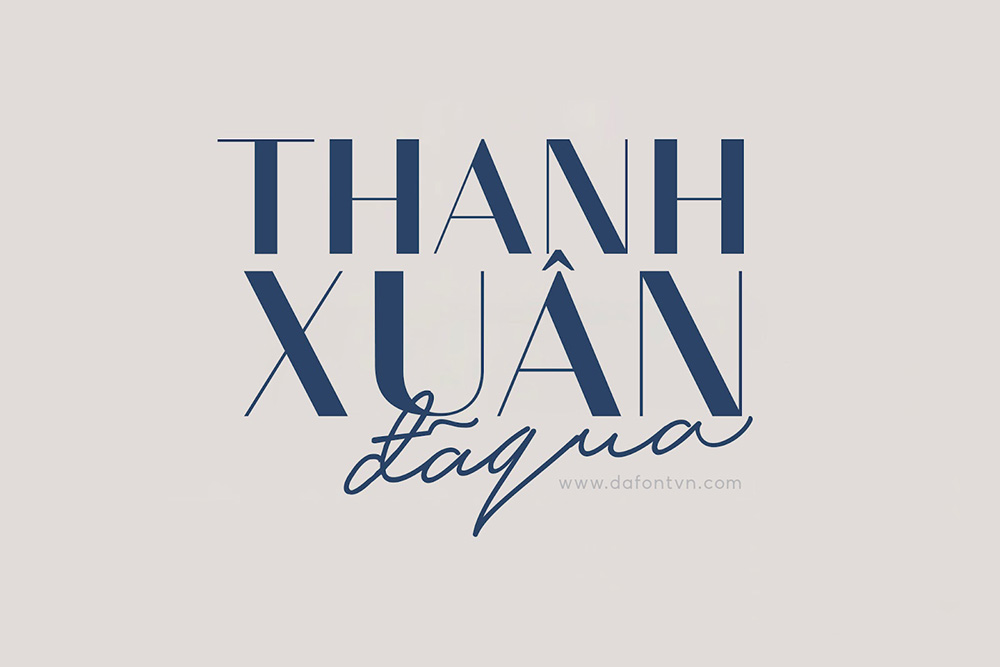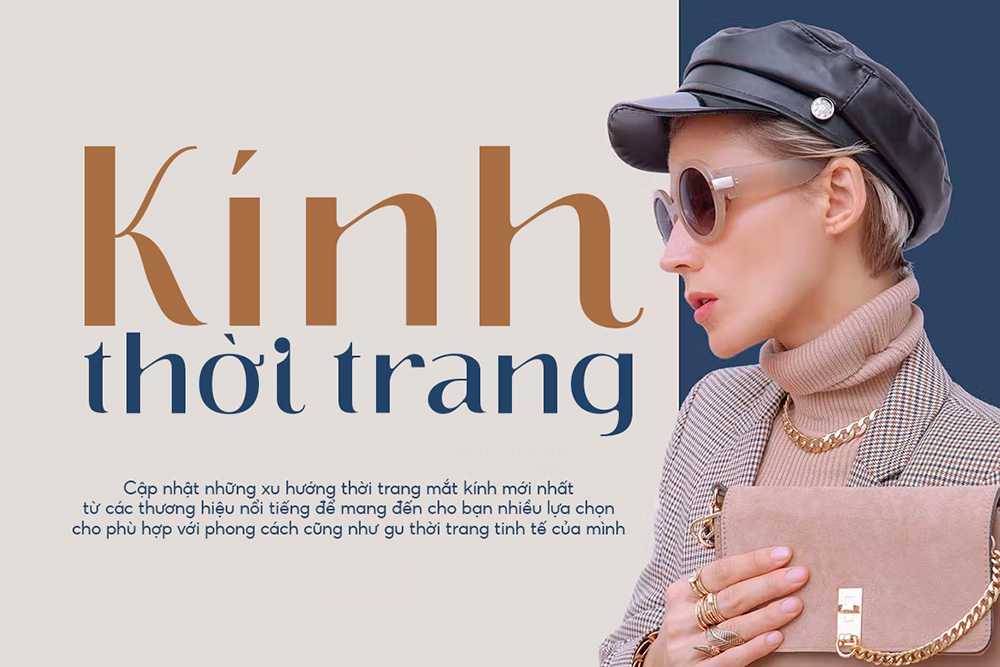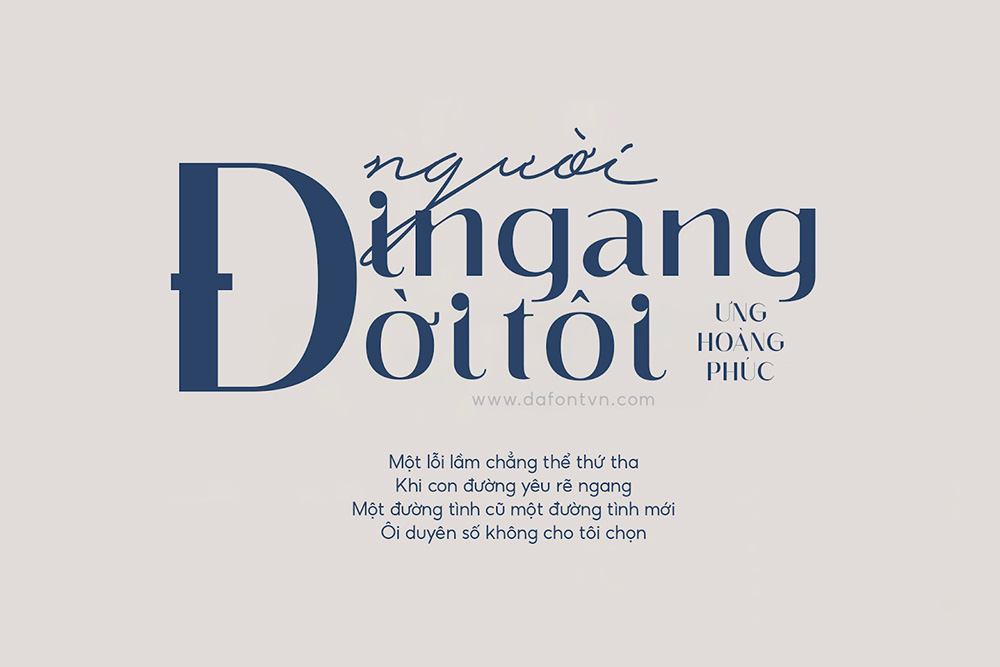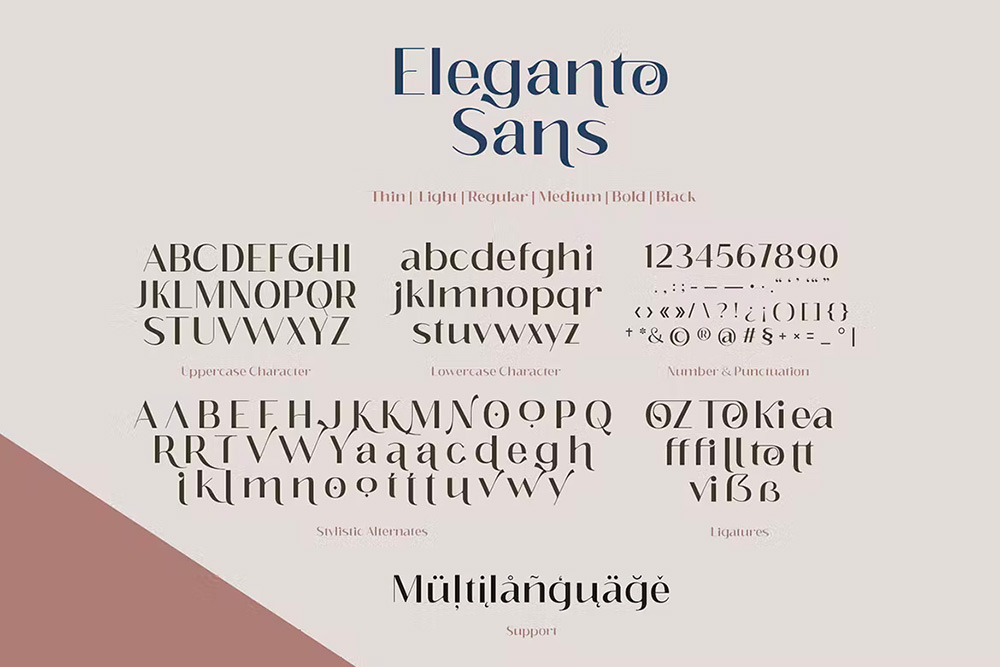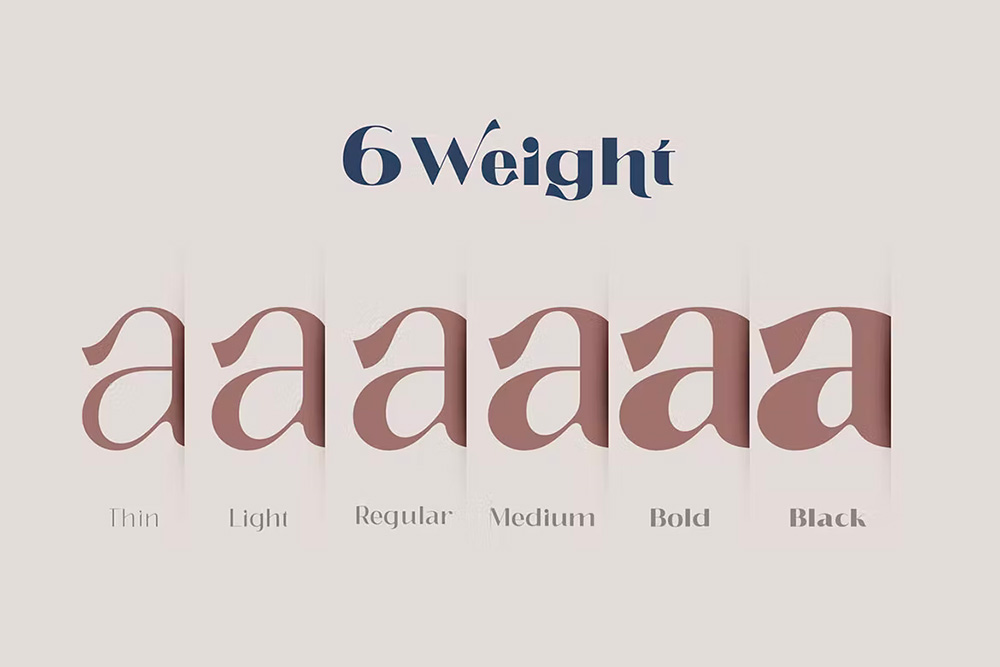
Font Việt Hóa - Eleganto Cực Đẹp Hiện Đại Hợp Thời Trang
Eleganto Sans font hiện đại hợp thời trang với các chữ thay thế đặc biệt, được thiết kế các đường nét quyến rũ và gợi cảm phù hợp cho hầu hết các thiết kế như xây dựng thương hiệu, tạp chí, thời trang, nhà hàng,...